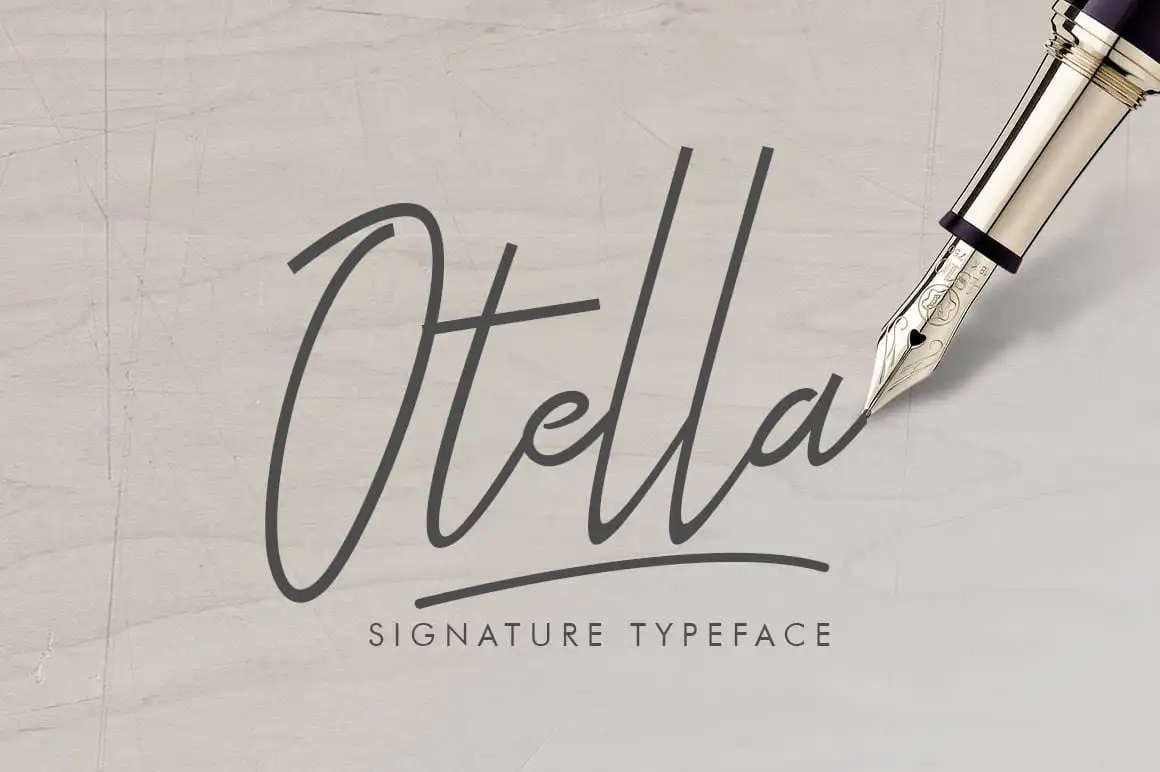
A Otella Signature Font é uma escolha única para designers que desejam adicionar um toque pessoal a seus projetos. Introduzida pela Khurasan, esta fonte script é um design original que oferece uma presença distintiva e singular. Com seu design almost monoline e sua tipografia de apenas um traço muito fino, Otella Signature captura a essência do estilo de escrita elegante. Seja para criar letras de e-mail personalizadas ou artigos de blog cheios de vida, esta fonte traz uma personalidade única que certamente deixará seu impacto. A introdução da otessa em sua obra tornará cada projeto mais vívido, com um design fresco e distinto que combina perfeitamente tanto para elementos de layout quanto para o corpo do texto. Na categoria de fonts script, Otella Signature é uma opção incrível para quem busca estilo, personalidade e expressividade.